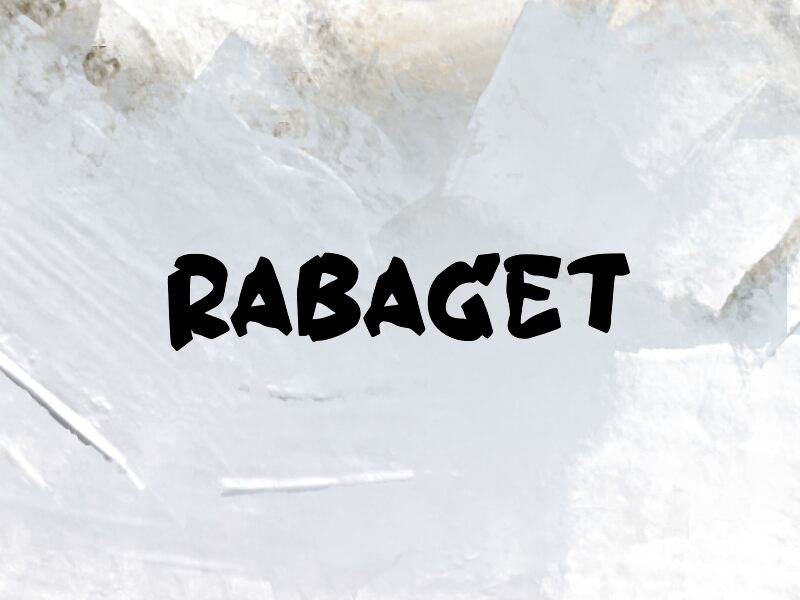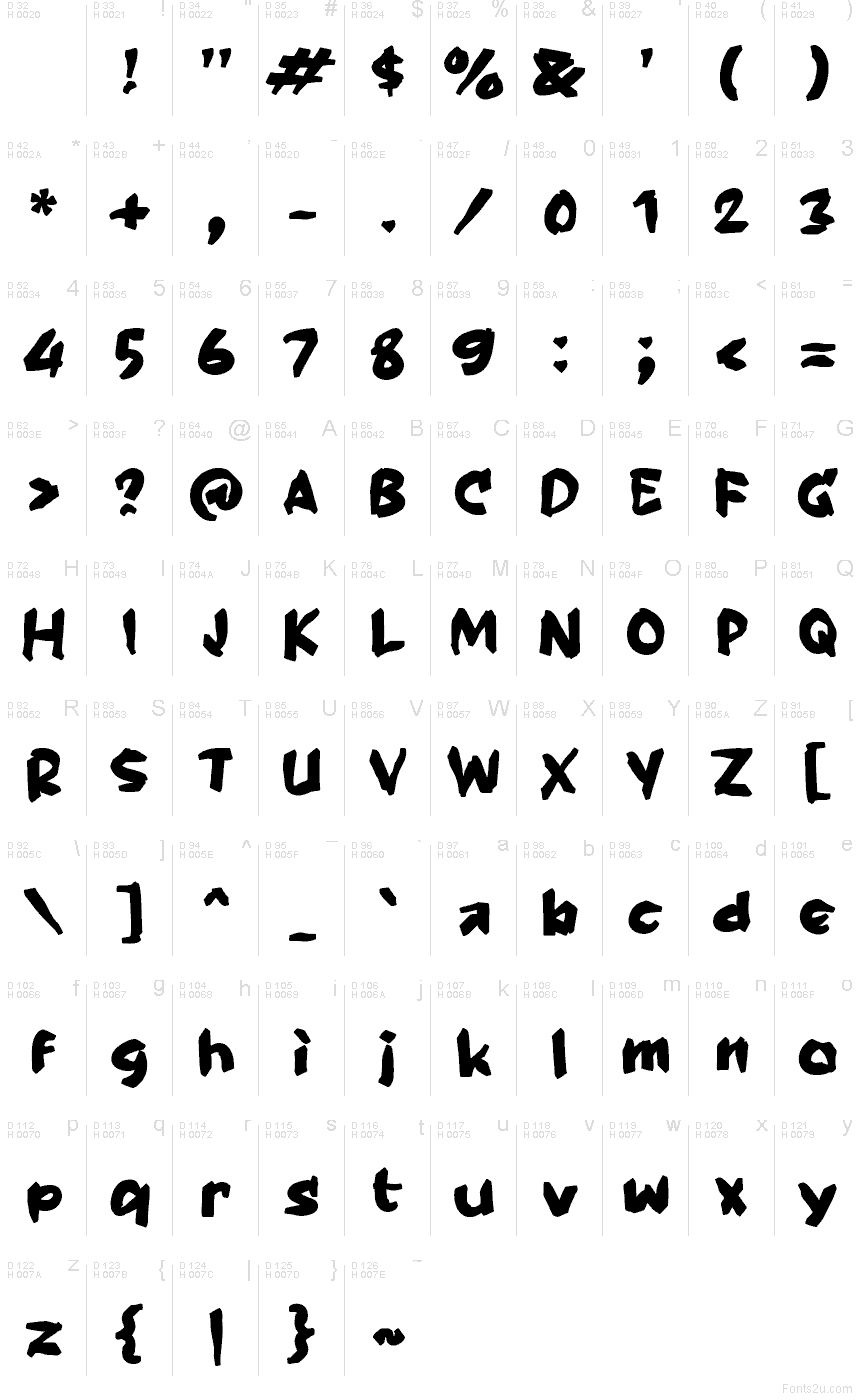
Rabaget da Wep é uma fonte graffiti gratuita com a energia bruta e direta de um lettering rápido feito a marcador na parede. As letras exibem formas robustas e irregulares, com cantos serrilhados, bordas irregulares e grandes aberturas que mantêm o estilo cru, nada polido.
Essa vibração rústica torna-a uma escolha natural para gráficos de streetwear, flyers de música, títulos de posters e branding de skate, onde uma palavra curta precisa de uma silhueta marcante. Sendo uma fonte gratuita, também funciona muito bem em cartões de título e monogramas, já que as suas formas largas e esculpidas destacam-se quando deixas que as letras falem por si.
Rabaget